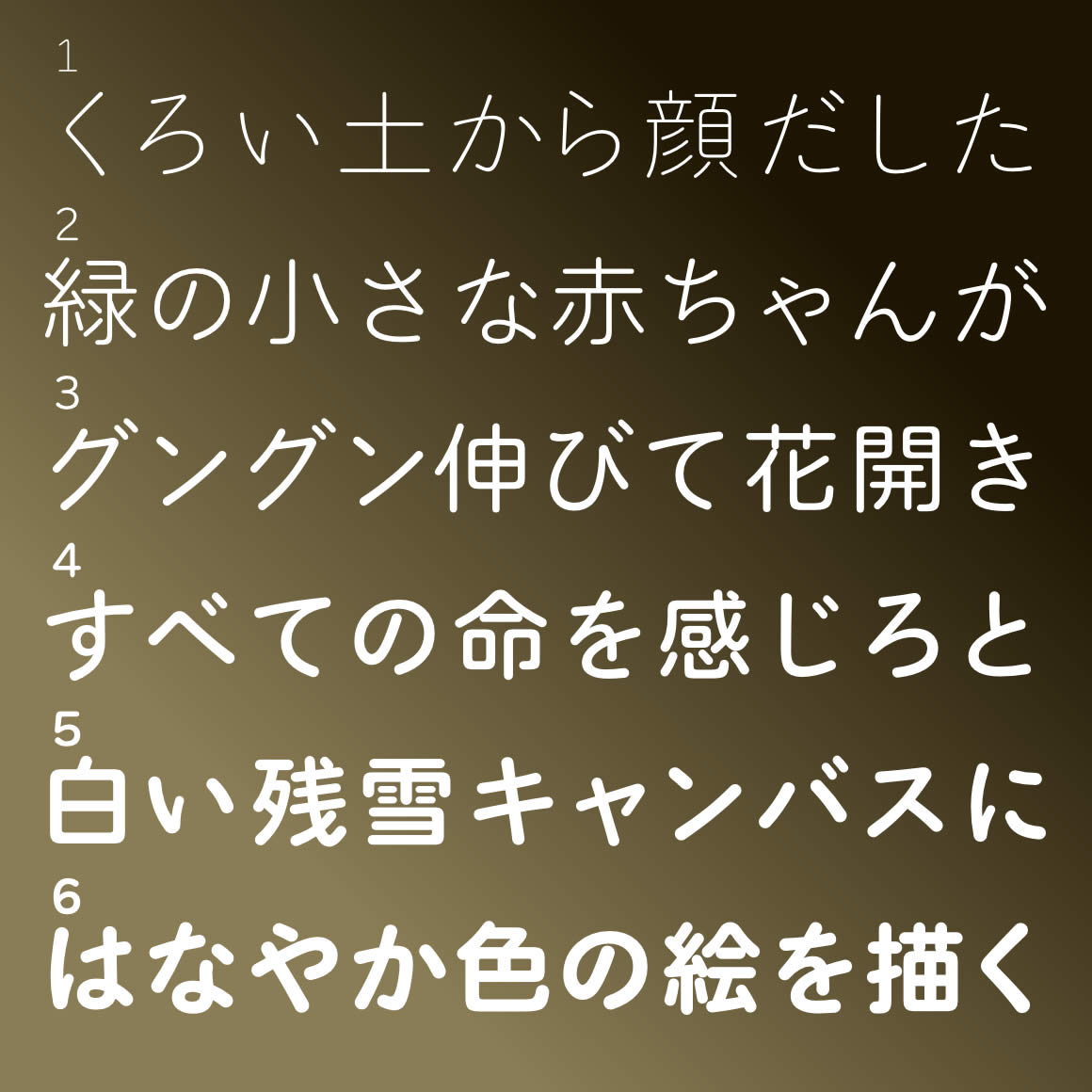
デザイン 古典的なカタチが美しい丸ゴシックかな書体「墨東丸」と、
プレーンなイメージの丸ゴシック書体「レラ」を組み合わせました。
マジメで読みやすい、新鮮なイメージを創り出すと思います。
等幅バージョンは、英大文字のアイ「I」と英小文字のエル「l」数字のいち「1」や、英大文字のオー「O」と数字のゼロ「0」が、はっきり区別がされているので、URL表記やプログラム編集などにぴったりです。
NEC特殊文字とIBM拡張文字も使えます。
連想されるイメージ
寄せられたコメントから抜粋
文字に力がある・マジメ・バランスが良い・読みやすい・やさしい・柔らかい・上品・本格っぽい・姿勢が良い